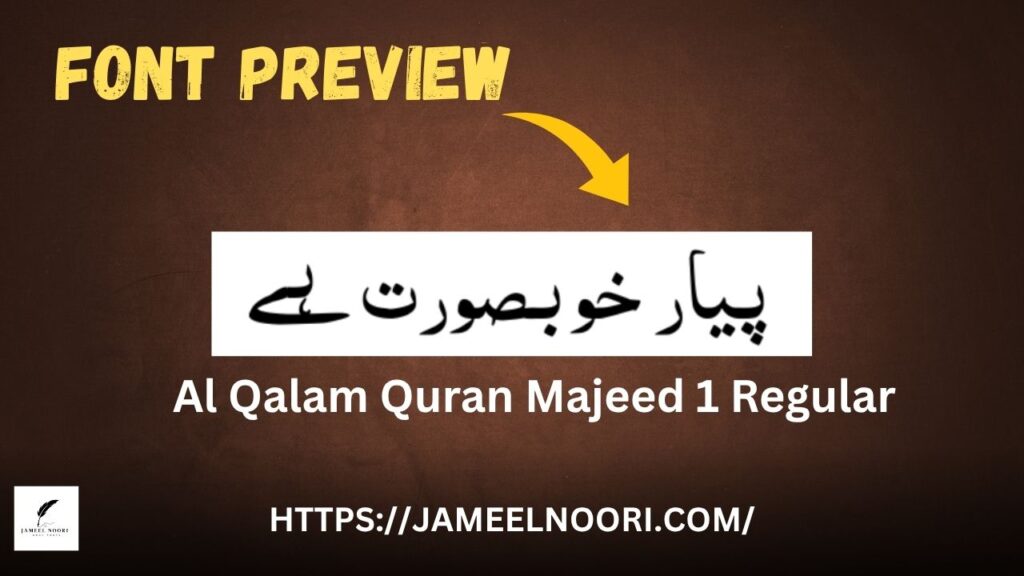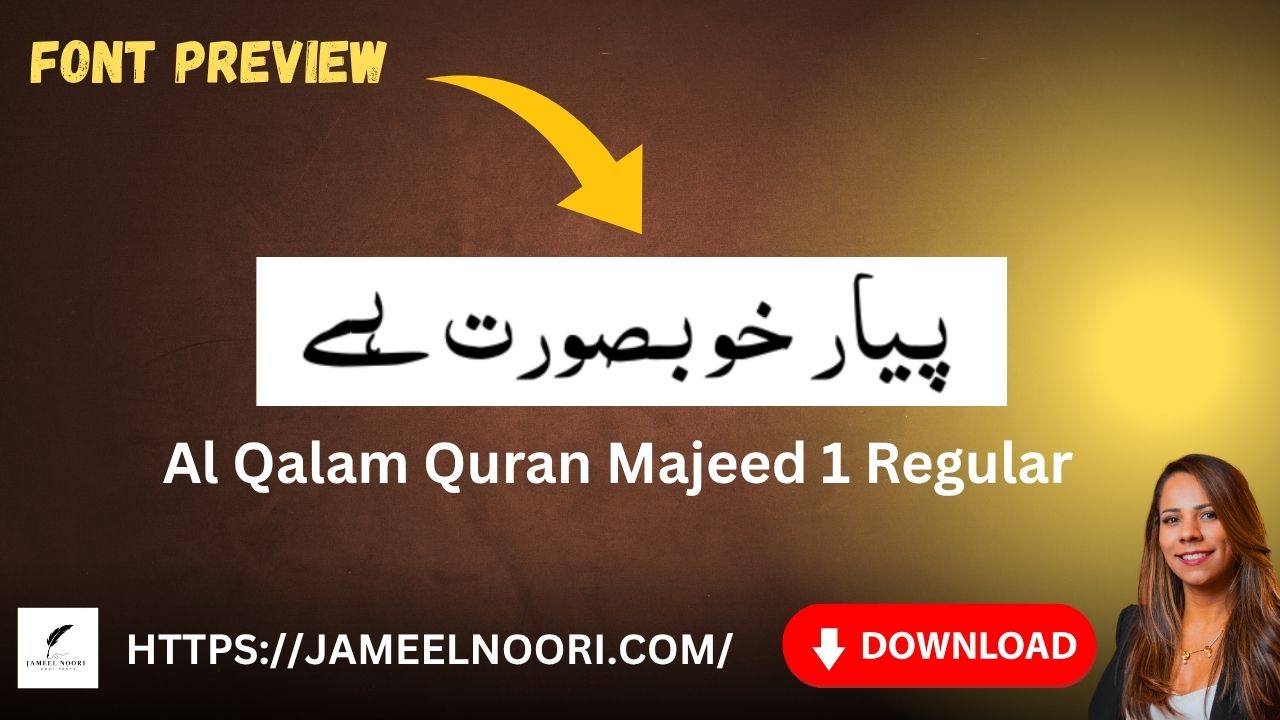
Urdu Font Al Qalam Quran Majeed 1 Regular ek mashhoor aur stylish TrueType font hai jo khas tor par Arabic aur Urdu Quranic text likhne ke liye design kiya gaya hai. Yeh font na sirf professional appearance deta hai balkay readability aur beauty dono me behtareen hai. Is article me hum apko is font ke bare me complete information dy gy taki aap bina time waste kiye is font ka best use kar saken.
What is Urdu Font Al Qalam Quran Majeed 1 Regular?
Urdu Font Al Qalam Quran Majeed 1 Regular aik free TrueType font hai jo mostly Quranic scripts, Urdu writing aur Islamic design projects me use hota hai. Iska design Arabic Nastaleeq aur modern calligraphy ka perfect combination hai. Yeh font Pakistan me bohot mashhoor hai aur designers aur students dono ke liye ideal hai.
Features of Urdu Font Al Qalam Quran Majeed 1 Regular
Is font ka smooth structure aur elegant curves Quranic ayats aur Urdu scripts ke liye perfect hain.
Why Choose Urdu Font Al Qalam Quran Majeed 1 Regular for Your Projects
Agar aap Islamic content, Quran apps, ya Urdu design projects banate hain, to yeh font aapke liye best choice hai.
Iska professional look aur balanced spacing text ko clear aur readable banata hai.
Highlights:
- Stylish and elegant Arabic script
Benefits of Using Urdu Font Al Qalam Quran Majeed 1 Regular
Yeh font un logon ke liye ideal hai jo readability aur elegance dono chahtay hain.
Key Benefits:
- Quranic text ke liye perfect spacing
- Beautiful Nastaleeq-inspired design
Expert Tips for Using Urdu Font Al Qalam Quran Majeed 1 Regular
Urdu Font Al Qalam Quran Majeed 1 Regular ek complete solution hai un sab ke liye jo Urdu aur Quranic fonts me elegance aur clarity dhoondte hain. Yeh font free hai, professional quality ka hai aur har designer ke liye must-have hai.
Does this font support Arabic and Urdu both?
Yes, it supports both Urdu and Arabic script seamlessly.
What makes this font special for Quranic use?
Its clear structure and classic calligraphy make it perfect for Quranic verses.